【Webフォントサービス「TypeSquare」まとめ記事】最新情報:統一感あるWebの多言語対応を可能にする書体「Clarimo UD」が追加
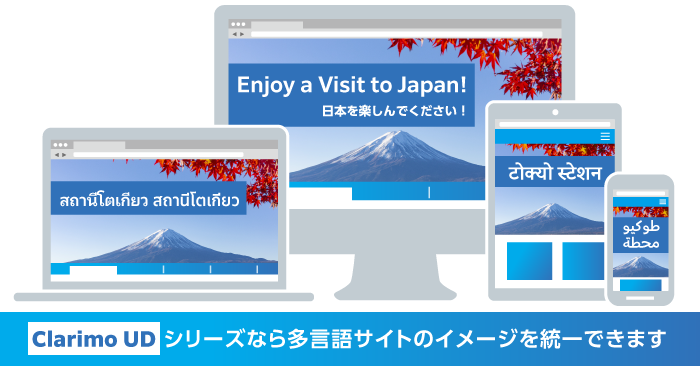
モリサワは、2019年11月7日(木)からWebフォントサービス「TypeSquare」に「Clarimo UD PE」「Clarimo UD Arabic」「Clarimo UD Devanagari」「Clarimo UD ThaiModern」を追加したことを発表した。
「TypeSquare」に今回、新たに追加される書体は、和文、簡体字、繁体字およびハングルまで展開されている「UD新ゴ」シリーズとの併記を目的として作られたサンセリフ書体で、シンプルかつ可読性を重視した設計を特徴としている。
それぞれの文字に精通した海外デザイナーが制作に携わり、高品質で統一感のある表現を可能にしているため、多言語対応したWebサイトも同じトーンの文字で表示できる。
東京五輪も迫る中、Webフォントサービス「TypeSquare」に「UD新ゴ 繁体字 標準字体」「UD黎ミン ハングル」が追加
東京オリンピック公式フォントとして東京オリンピックに協賛しているモリサワが東京五輪を見据える上での一手かモリサワは、2019年5月13日(月)よりWebフォントサービス「TypeSquare」に「UD新ゴ 繁体字 標準字体」「UD黎ミン ハングル」を追加したことを発表した。
2019年5月13日に新たに追加した書体は、和文書体UD新ゴのデザインをベースに設計され、台湾、香港、マカオでの中国語表記をサポートする「UD新ゴ 繁体字 標準字体」と和文書体UD黎ミンのデザインをベースに設計された明朝体で柔らかいエレメント、直線的なストローク、可読性が特徴的な「UD黎ミン ハングル」の2書体となる。
グローバル展開する企業などで、日本・海外のWebサイトで一巻した書体デザインを使用したい場合に有用そうだ。
モリサワのWebフォントサービス「TypeSquare」に「A1ゴシック」「凸版文久見出し明朝 EB」「秀英角ゴシック金 M」「秀英角ゴシック銀 M」が2018年9月に追加
モリサワが提供しているWebフォントサービス「TypeSquare」に、新書体として「A1ゴシック」「凸版文久見出し明朝 EB」「秀英角ゴシック金 M」「秀英角ゴシック銀 M」が2018年9月10日に追加された。
秀英角ゴシック金、秀英角ゴシック銀は今回、既に提供されているウエイトに加えて、新たなウェイト「M」が追加された形となる。
A1ゴシック
A1ゴシックは、A1明朝の基本となる骨格を参照して作成されたオールドスタイルのゴシック体。線画の交差部分の墨だまり表現や、エレメントの端々に僅かな角丸処理が施された温もりを感じるデザインになっている。
凸版文久見出し明朝 EBをモリサワのフォントシミュレーションで
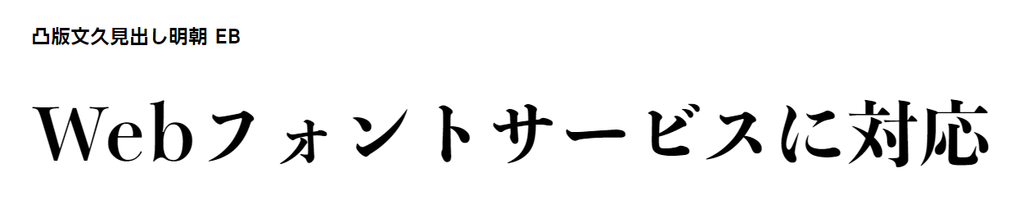
凸版文久見出し明朝 EBは、勢いのある運筆が特徴の見出し用明朝体で、従来の凸版書体とその源流である築地体の骨格をベースにデザインされている。Webサイトでも見出し書体らしい、確かな存在感を発揮する。
モリサワのWebフォントサービス「TypeSquare」
「TypeSquare」はモリサワのWebフォントサービス。モリサワが提供するサービスなので当然、主にモリサワフォントがWebフォントとして使えるサービス。
Webフォント
Webフォントはインターネットを介してフォントを配信し、Webブラウザで表示させる仕組みを意味する。
Webフォントを使ったWebサイトは、閲覧側に指定されたフォントが搭載されていなくても、制作側で指定された書体が表示される。
PCだけでなく、スマートフォンやタブレットなどのWebブラウザでの表示も可能。
TypeSquareでエイワンとデザインシグナルのフォントがWebフォントに
モリサワが展開するWebフォントサービス「TypeSquare」に、8月22日(火)から「ZENオールド明朝 N」などのエイワン書体や「きりぎりす」などのデザインシグナル書体が使用できるようになった。
シンプルで使い勝手の良いラインナップが特徴で、キャッチコピーから本文用途まで幅広いシーンで利用されている。
個性が際立つデザイン系書体を数多く取り揃え、ゲームやパッケージデザインなどさまざまなジャンルで見る人の目を引きつける、特にきりぎりすは至る所で目にする書体なので、Webフォントとしてどう使用されるのか興味が尽きない。
エイワンとデザインシグナルのWebフォントをトライアウトしてみた!
DSきりぎりすにするとかわいい印象になる。
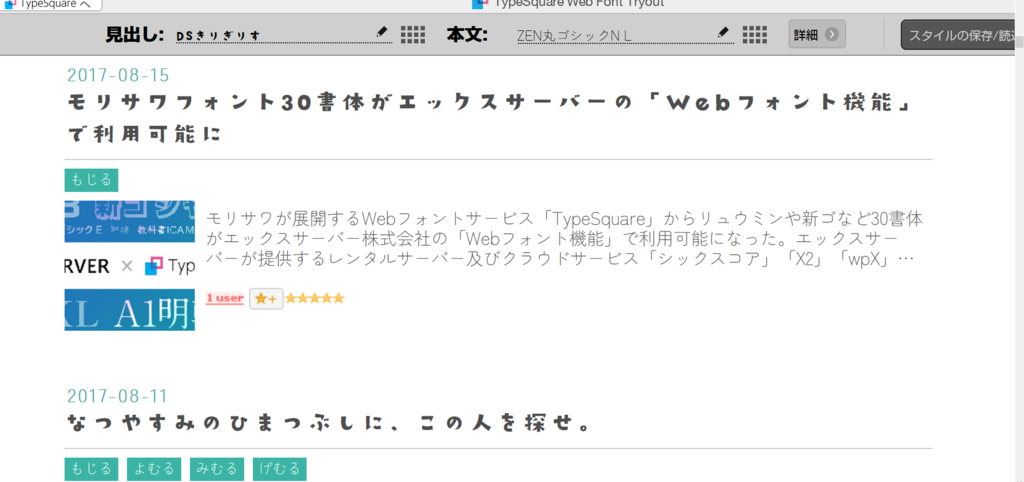
ZEN書体も確かに本文で読みやすい。
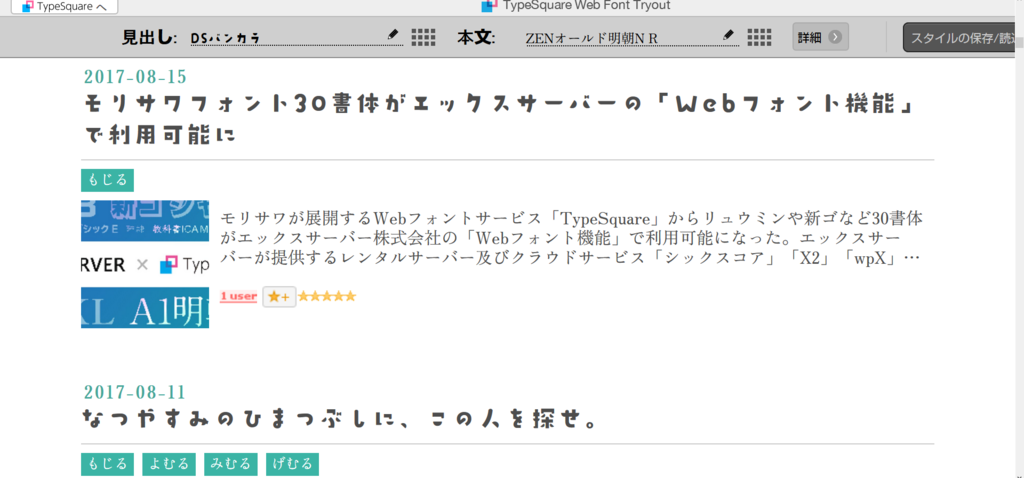
書体の選択肢が広がり、更に色々な組み合わせが楽しめるようになった。
今回のWebフォントサービス「TypeSquare」での書体提供は始まりに過ぎず、エイワンとデザインシグナルの書体がモリサワパスポートに収録される計画で合意しているのかもしれないと邪推する。
近年モリサワが力を入れているデザイン書体のカテゴリー枠の更なる拡充として、デザインシグナル書体が追加されれば、モリサワパスポートユーザーにとっても朗報だ。